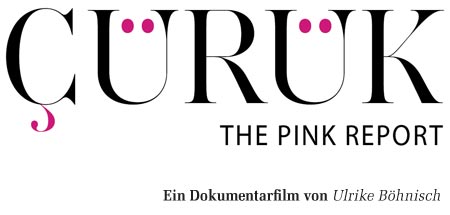
Suche Font / ähnlich caslon
Ich glaube fast, der Threaderöffner sucht einfach eine Schrift, die der Caslon ähnlich ist. Hilfreich wäre es für uns natürlich, wenn wir wüssten, warum die Caslon selber nicht geeignet ist, beziehungsweise, wodurch sich die gesuchte Schrift von der Caslon unterscheiden sollte: Preis? Ausbau? Verfügbare Zeichen? :-?
Wenn ich mich richtig erinner, stand da ein Logo eines Magazins, alles Versalien, zwei Ü dabei, wobei die Punkte lila innerhalb des U gesetzt waren und das C (?) am Wortanfang mit einem Cedilla oder Ogonek, ebenfalls in lila, versehen war.